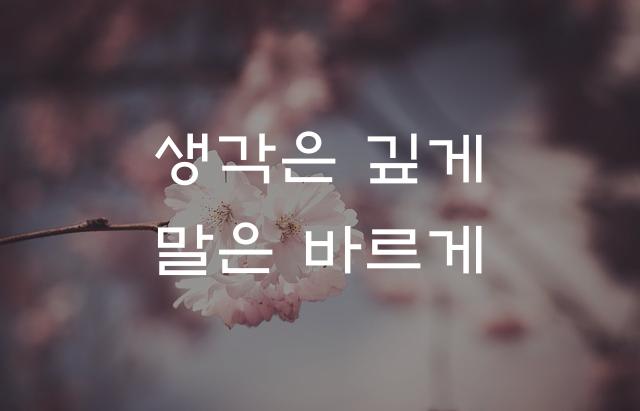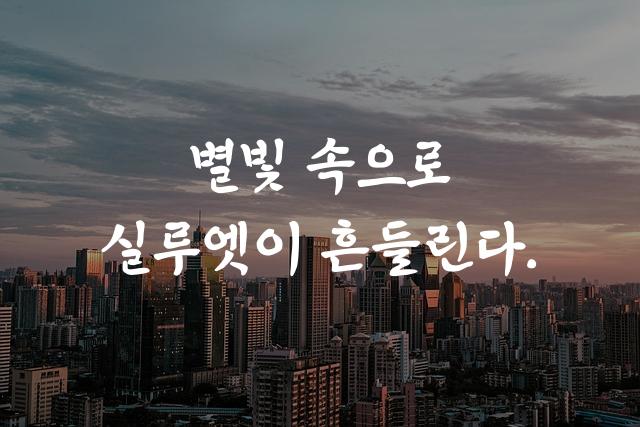
EBS훈민정음은 EBS에서 제작한 꽉 찬 고딕 스타일의 폰트로, 전통적인 한글의 아름다움을 현대적으로 재해석한 디자인입니다. 이 폰트는 강렬하면서도 정교한 느낌을 제공하여, 문서와 디자인 작업에 우아함과 역사적 가치를 더합니다.
EBS훈민정음은(는)
기본 고딕, 명조/전통, 레트로, 굵은 고딕, 복고풍, 단단함 계열의 생김새를 가지고 있으며
교육 자료, 보고서/문서 등에서 자주 활용되며, 효과적인 메시지 전달에 적합합니다.
이 폰트는 교육, 출판/미디어 분야에 잘 어울리며,
신뢰감, 명확한 느낌을 담고 있는 것이 특징입니다.